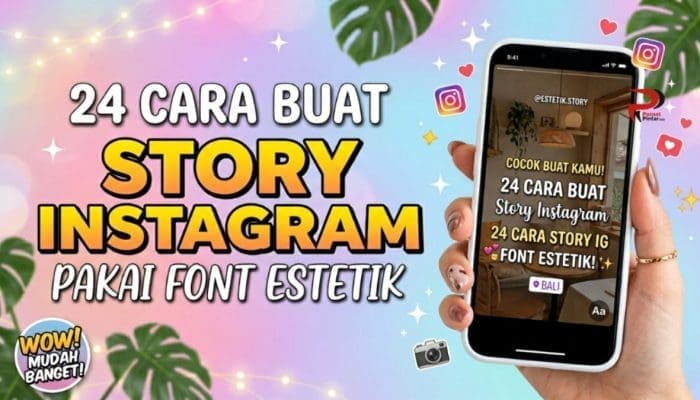
24 Cara Buat Story Instagram Pakai Font Estetik
Instagram menjadi salah satu media yang banyak digunakan untuk berbagi momen berharga, khusunya pada fitur story yang disediakan. Pengguna bahkan bisa melakukan edit lanjutan pada story dengan menggunakan tools yang tersedia.
Salah satu fitur yang banyak digunakan adalah fitur untuk mengubah font teks untuk caption pada story yang diunggah. Kamu bisa menggunakan berbagai jenis font yang telah disediakan pihak Instagram untuk mempercantik caption.
Namun, bagaimana jika kamu ingin menggunakan jenis font lain yang tidak tersedia pada daftar tersebut? Tidak perlu khawatir, kamu bisa menyimak artikel ini untuk menemukan solusi yang dapat digunakan.
24 Cara Buat Story Instagram Pakai Font Estetik Sbb:
Agar kamu bisa mendapatkan tulisan estetik yang nantinya dapat digunakan sebagai caption di story Instagram, kamu dapat menyimak 24 cara buat story Instagram pakai font estetik di bawah ini. Dalam hal ini, kamu membutuhkan situs online untuk membantu.
1. Cari Font Estetik di Convertmee.com
Convertmee.com menjadi salah satu situs serbaguna yang juga menghadirkan tools untuk mencari font estetik, unik, dan elegan. Salah satu alat yang bisa kamu akases untuk mendapatkan berbagai font estetik tersebut adalah Generator Teks Fancy. Berikut cara mengaksesnya”
• Klik “Generator Teks Fancy“
• Ketik caption yang ingin kamu buat pada kolom “Generate Text”
• Scroll ke bagian bawah untuk menemukan daftar font
• Tekan opsi “Copy” di samping font yang diinginkan
• Lalu, buat story Instagram dan tempel atau paste teks tadi
2. Cari Font Estetik di Generator Font Instagram
Ketuk “Generator Font Instagram” ini, dan temukan sejumlah font yang bisa kamu pilih untuk membuat story Instagram lebih menarik saat dilihat diri sendiri maupun orang lain. Cara mengakses tulisannya pun sama seperti langkah-langkah di atas.
3. Cari Font Estetik di Teks Simbol Keren
Untuk membuat story Instagram dengan tulisan estetik yang disertai dengan berbagai simbol keren, kamu bisa langsung mendapatkannya melalui alat “Teks Simbol Keren” ini.
4. Cari Font Estetik di Copy Paste Text
Sejumlah font bold, italic, dan descript dengan berbagai variasi bisa kamu dapatkan melalui “Copy Paste Text Online Generator“. Story Instagram akan terlihat lebih elegan jika kamu menggunakan font yang ada di sini.
5. Cari Font Estetik di Teks Simbol Berwarna
StoryInstagram bisa menjadi lebih berwarna dan menarik lagi jika kamu menambahkannya teks dengan simbol berwarna. Akses “Teks Simbol Warna” ini untuk melihat jenis font unik yang disediakan.
6. Cari Font Estetik di LingoJam
Pada situs LingoJam, kamu akan menemukan alat yang dapat membantumu menemukan sejumlah font estetik yang juga mendukung untuk mempercantik story Instagram.
7. Cari Font Estetik di TextFancy
Selain teks estetik, situs ini juga menyediakan berbagai text art hingga simbol menarik yang juga bisa digunakan, sama halnya seperti Convertmee.com
8. Cari Font Estetik di Foto Font Generator
Cari berbagai font estetik melalui situs ini untuk kamu copy dan paste di story Instagram.
9. Cari Font Estetik di Pretty Fonts Generator
Font estetik juga akan kamu dapatkan dengan mudah saat mengakses situs ini melalui browser.
10. Cari Font Estetik di Namecheap Italic & underline Font Generator
Sesuai namanya, kamu akan menemukan tulisan italic hingga tulisan tercoret melalui situs ini.
11. Cari Font Estetik di TextStudio
TextStudio menghadirkan teks unik di mana tulisannya bisa terlihat memiliki efek 3D.
12. Cari Font Estetik di YayText
Kunjungi situs YayText melalui browser yang terinstal di Hp-mu untuk menemukan berbagai pilihan font estetik.
13. Cari Font Estetik di FancyTextPro
FancyTextPro dirancang untuk membantu pengguna menemukan teks klasik hingga simbol keren.
14. Cari Font Estetik di Metatags
Antarmukanya yang bersih akan membuatmu lebih mudah memahami bagaimana cara untuk mengakses teks estetik yang disediakan di dalamnya.
15. Cari Font Estetik di Sprezz
Akses situs Sprezz agar kamu bisa emilih font estetik yang mungkin bisa membuatmu tertarik untuk digunakan di story Instagram.
16. Cari Font Estetik di Messletters
Messletters akan membantu membuat tulisan biasa menjadi gaya acak yang terlihat estetik.
17. Cari Font Estetik di MegaCoolText
Tidak hanya teks estetik saja yang akan kamu temukan di sini, tetapi juga handwritter yang keren.
18. Cari Font Estetik di FontGen IN
Teks standar bisa kamu ubah dengan mudah saat mengunjungi situs FontGen IN ini.
19. Cari Font Estetik di CoolText
Website lainnya yang juga bisa kamu gunakan untuk mencari font estetik adalah CoolText.
20. Cari Font Estetik di OpenL Fancy Text Generator
Hanya dengan mengetikkan caption yang diinginkan, tlisan tersebut akan langsung diubah menjadi teks estetik dan unik.
21. Cari Font Estetik di Inflact Aesthetic Text Generator
Salah satu situs yang juga dapat kamu manfaatkan untuk menemukan teks unik adalah situs Inflact Aesthetic Text generator ini.
22. Cari Font Estetik di Creative Fabrica Aesthetic Fonts Generator
Vibes story Instagram akan erasa lebih estetik dan keren jika kamu menemukn font sesuai di situs satu ini.
23. Cari Font Estetik di IGFonts
IGFonts dirancang khusus untuk menampilkan font estetik yang nantinya dapat digunakan sebagai font story Instagram yang lebih memukau.
24. Cari Font Estetik di Picsart Font Generator
Picsart adalah platform yang banyak digunakan untuk melakukan pengeditan foto lanjutan. Namun platform ini juga memiliki fitur yang bisa digunakan untuk edit foto dengan font estetik.
Sekian 24 cara buat story Instagram pakai font estetik agar vibes story tersebut terlihat lebih memukau. Semoga informasi yang diberikan di atas dapat membantumu menemukan font estetik yang ingin digunakan.